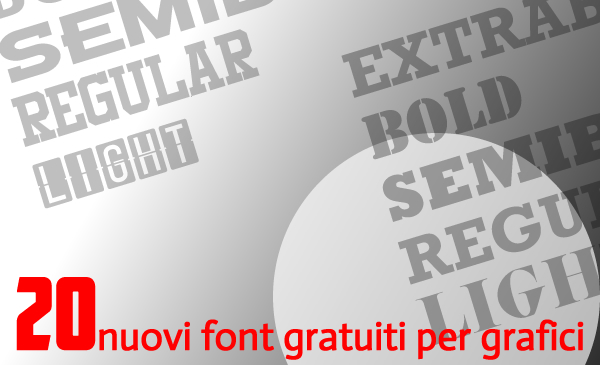
Questi font sono perfetti per qualsiasi progetto per dare un aspetto magnifico e professionale a intestazioni e titoli.
Questi font sono ideali per loghi e marchi, inviti, cancelleria, design di matrimoni, post sui social media, poster pubblicitari, packaging di prodotti, design di prodotti, etichette, fotografia, filigrane, eventi speciali e molto altro.
20 nuovi font gratuiti per grafici